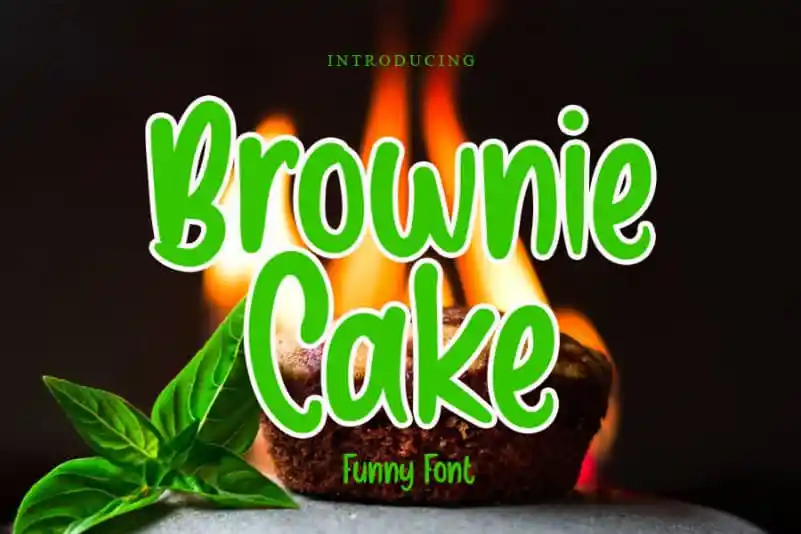
Brownie Cake Display Font – Fonte Grátis
Brownie Cake Display Font
A fonte ‘Brownie Cake Display Font’ é uma fonte escrita a mão casual, perfeitamente adequada para aqueles que desejam um toque descontraído e criativo em suas criações. Com seu estilo simples e fácil de usar, esta font será uma adição maravilhosa aos seus designs de crafts diversas, transformando-os em algo ainda mais único e bonito. Seja você um designer ou um entusiasta dos artesanatos, a ‘Brownie Cake Display Font’ é uma escolha perfeita para aqueles que valorizam tanto o design moderno quanto a personalização única. Engane-se se acreditar que ela foi criada apenas para decorações de chá caseiras; este font irá brilhar em qualquer tipo de projeto gráfico, seja ele um site elegante ou uma camiseta despojada e divertida. O levincreative trouxe-lhe isso com toda a sua simplicidade e encanto.